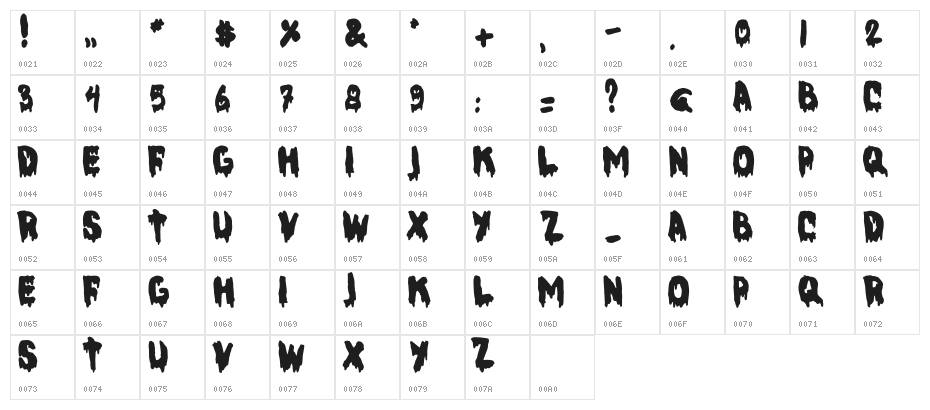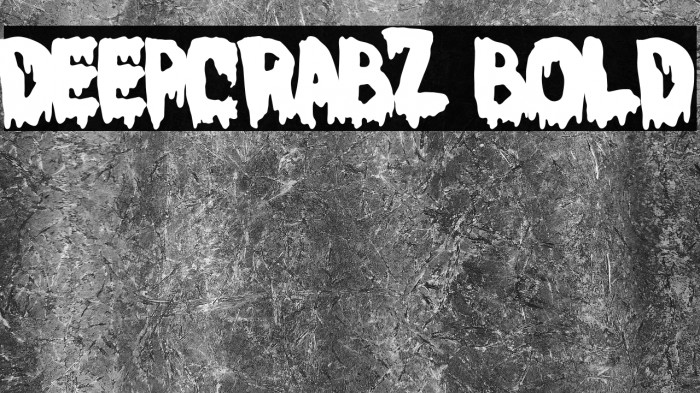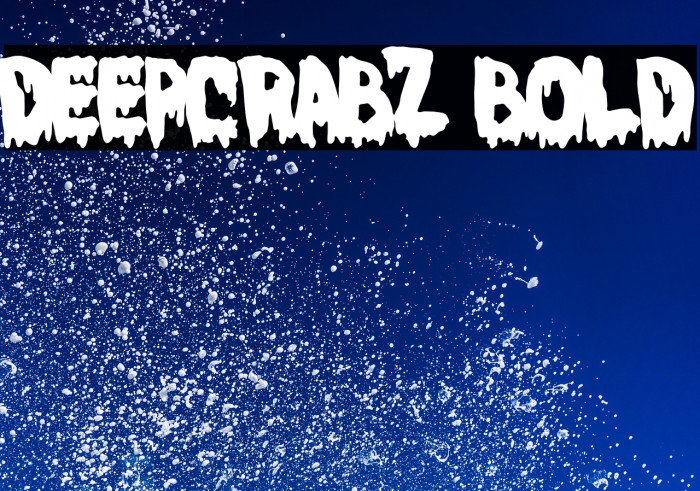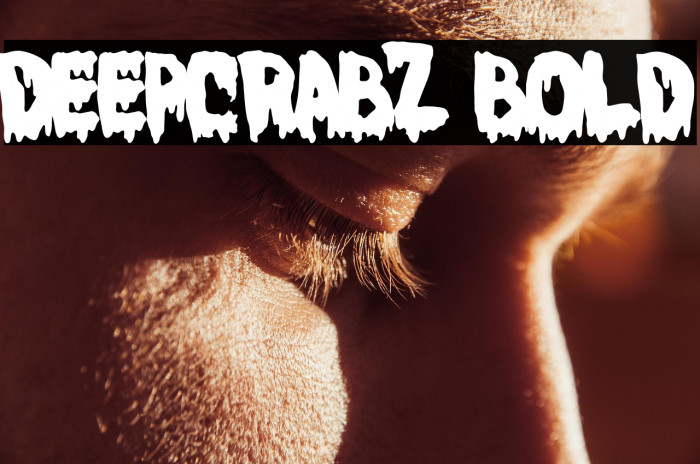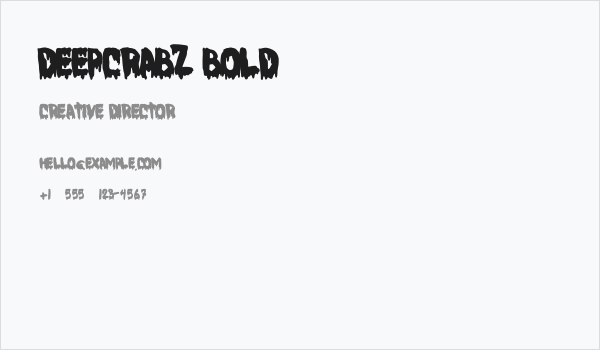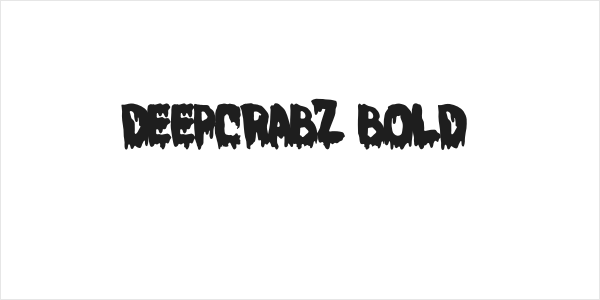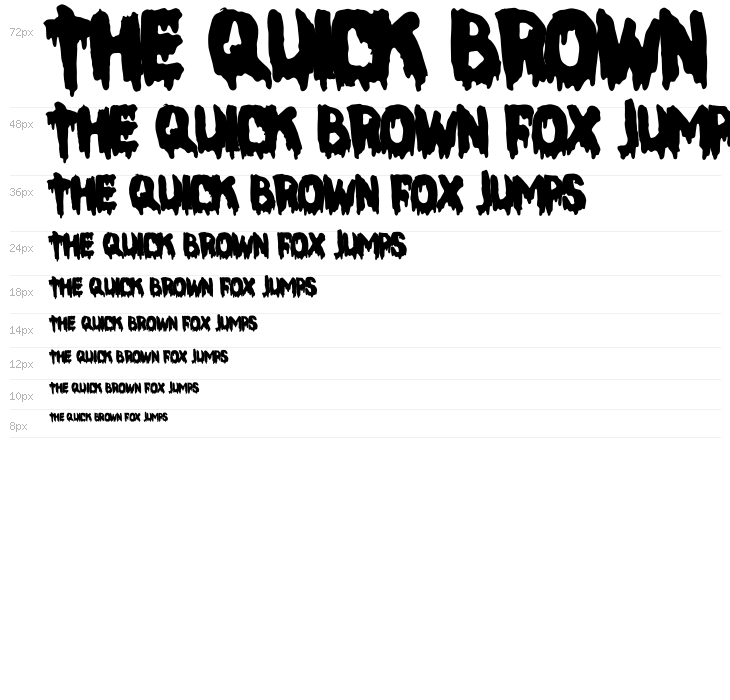
DeepCrabz Bold Font
| Progetti proposti | Ideal for horror-themed designs, Halloween posters, edgy branding, or any project needing a bold, eye-catching typeface. |